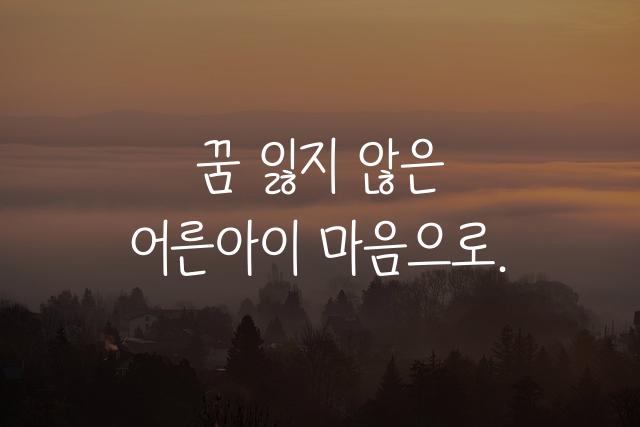
Continuous
‘Continuous’는 이범석 제작사에 의해 디자인된 캘리그라피 스타일의 영문 필기체 폰트입니다. 부드럽고 연속적인 필기 느낌이 특징이며, 감성적인 표현이 가능해 개인적인 메시지나 창의적인 작업에 적합합니다.
이범석
이 폰트의 인사이트!
감성적, 부드러운, 개성적
Continuous은(는) 손글씨, 펜/붓터치, 감성적인 계열의 생김새를 가지고 있으며
로고 디자인, 웹/앱 디자인, 브랜딩 등에서 자주 활용되며, 효과적인 메시지 전달에 적합합니다.
이 폰트는 광고/마케팅, 크리에이티브, 기술/IT 분야에 잘 어울리며,
세련된, 창의적인, 전문적인 느낌을 담고 있는 것이 특징입니다.
이 폰트와 유사한 폰트로는 Brush Script, Lucida Handwriting, Pacifico 등이 있어요. 함께 비교해 보시면 좋습니다!